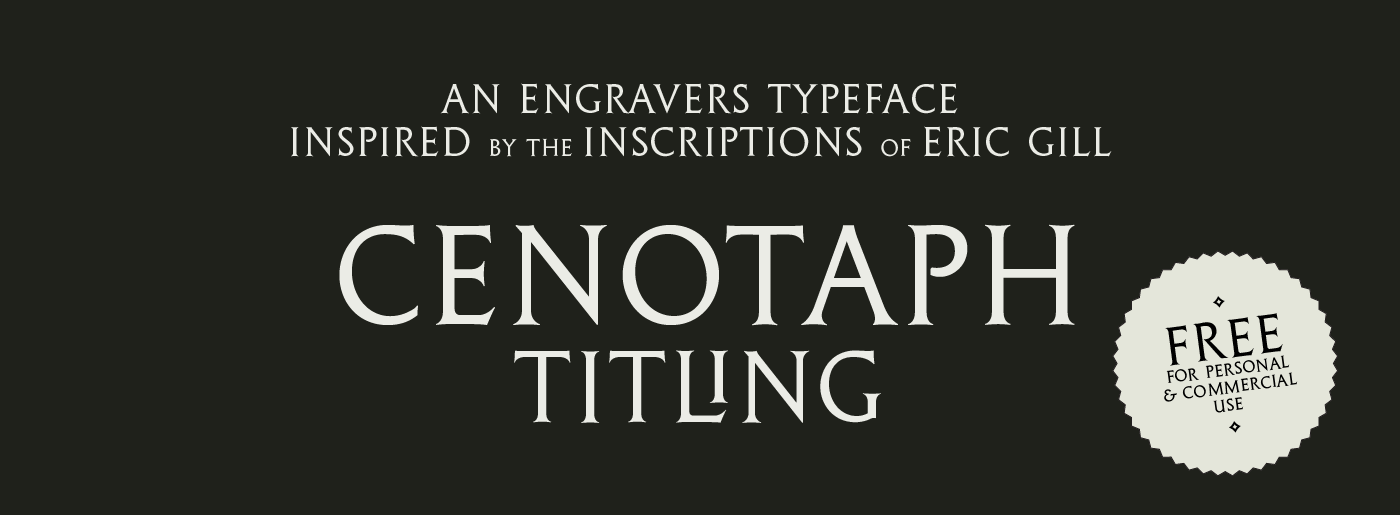
Cenotaph Titling Font – Download Grátis
A Cenotaph Titling Font é uma tipografia serifada inspirada no estilo de inscrições feitas por Eric Gill, um renomado designer gráfico inglês conhecido especialmente pelo seu trabalho com materiais como cerâmica e metal. Esta fonte exibe características de títulos marcantes que remetem diretamente à sua origem naqueles registros enigmáticos criados pelo próprio Gill. O nome “Cenotaph” refere-se ao tipo específico de sepultura usada quando uma pessoa é enterrada em um local diferente do seu lugar de nascimento. Similhar a este significado, esta fonte traz uma sensação elegante e monumental que complementa os títulos mais importantes em qualquer projeto gráfico. O designer Hamilton trouxe o estilo de inscrições de Eric Gill à vida através da tipografia, particularmente na vertical do “U”. Esta característica é um lembrete de como a Cenotaph Titling Font se conecta à tradição e ao design clássico. Através desta fonte, você pode expressar seus ideais com elegância e estilo único em qualquer projeto gráfico que possa exigir uma tipografia serifada.